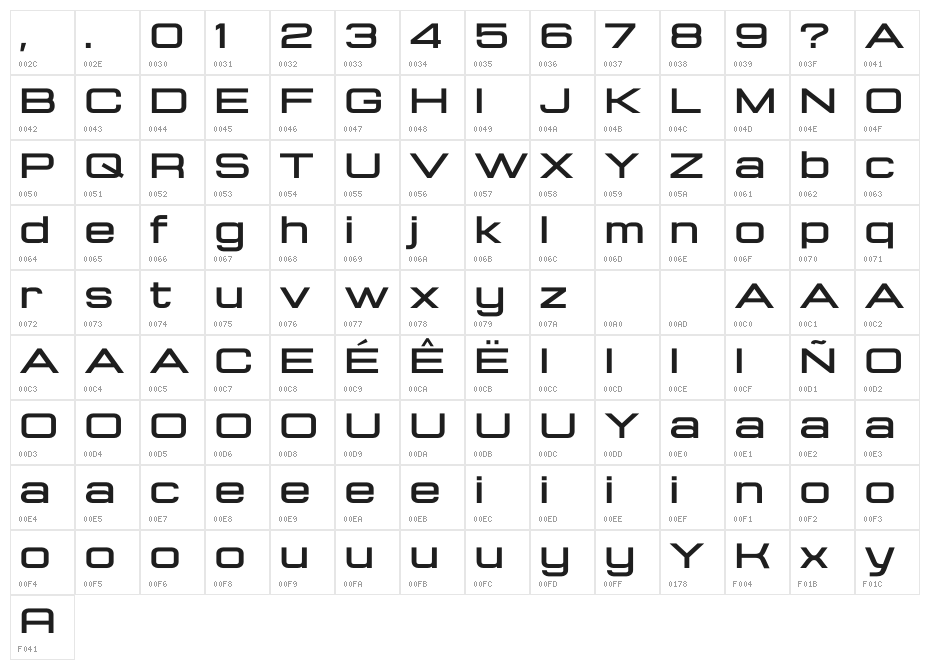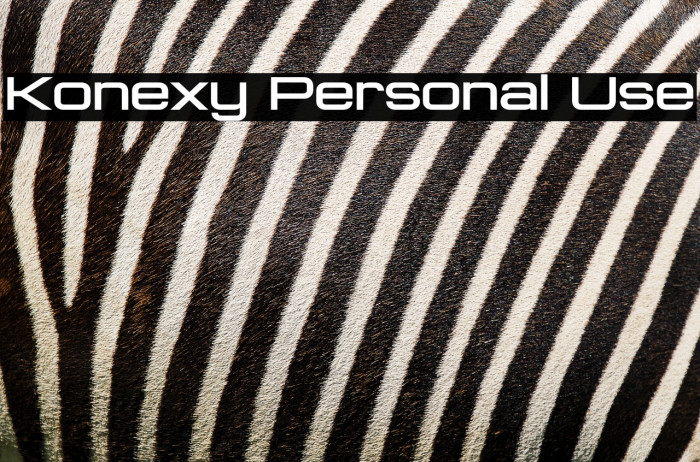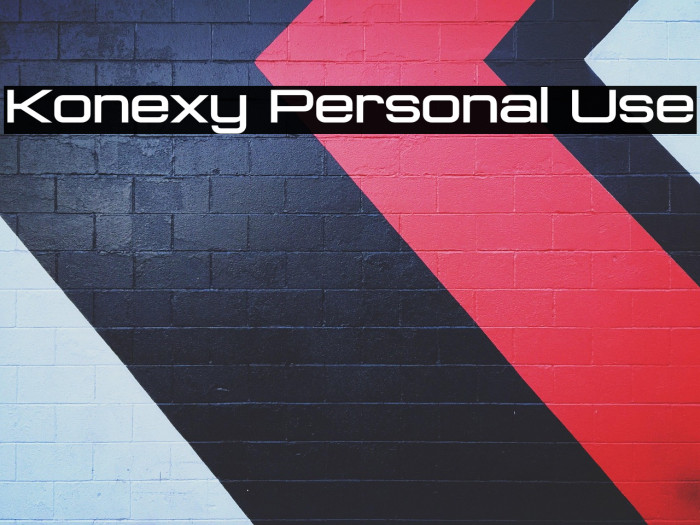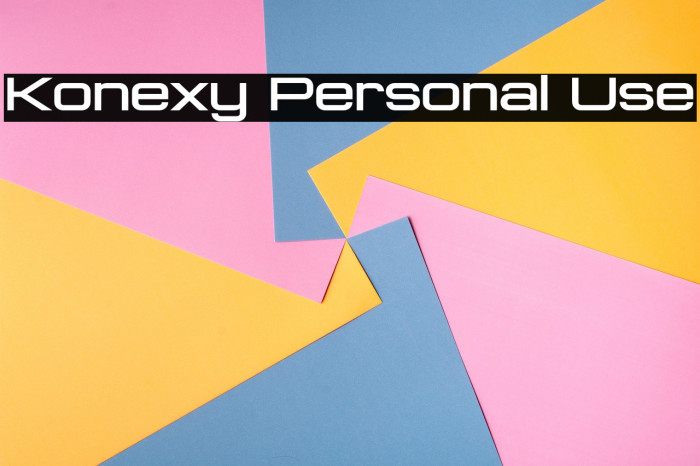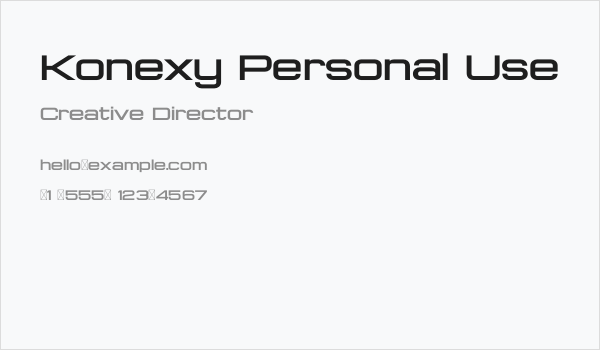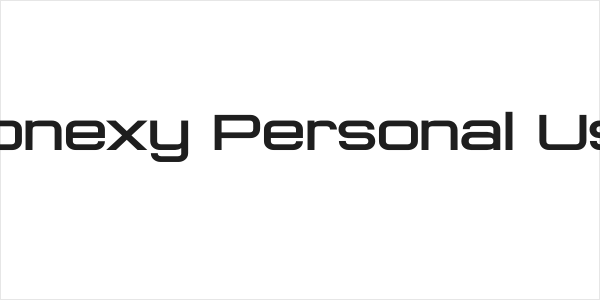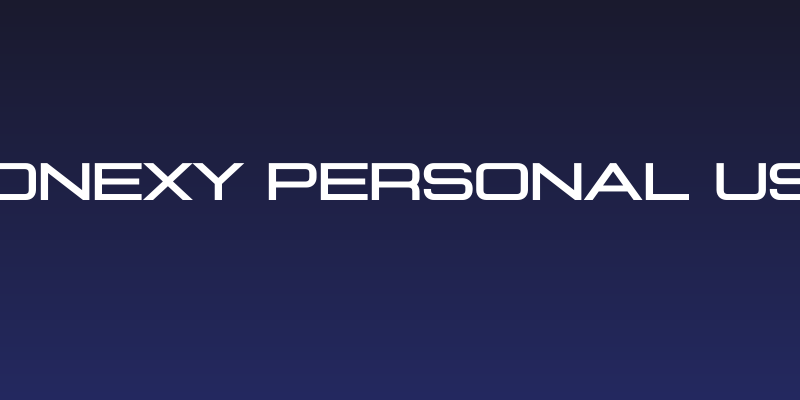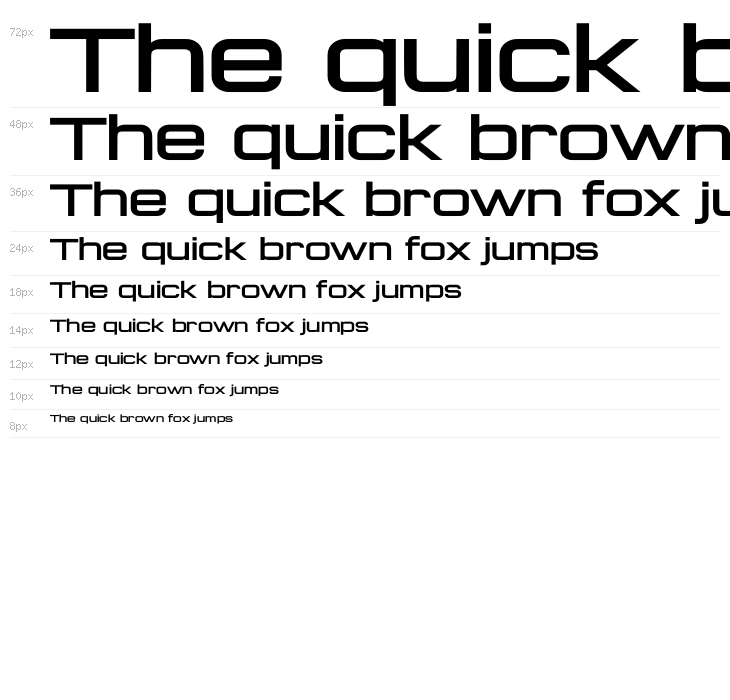
Konexy Personal Use Font
| Anwendungsfall | Headlines, Logos, Digital Interfaces |
| Vorgeschlagene Projekte | Ideal for technology branding, modern advertising, and digital interfaces. |